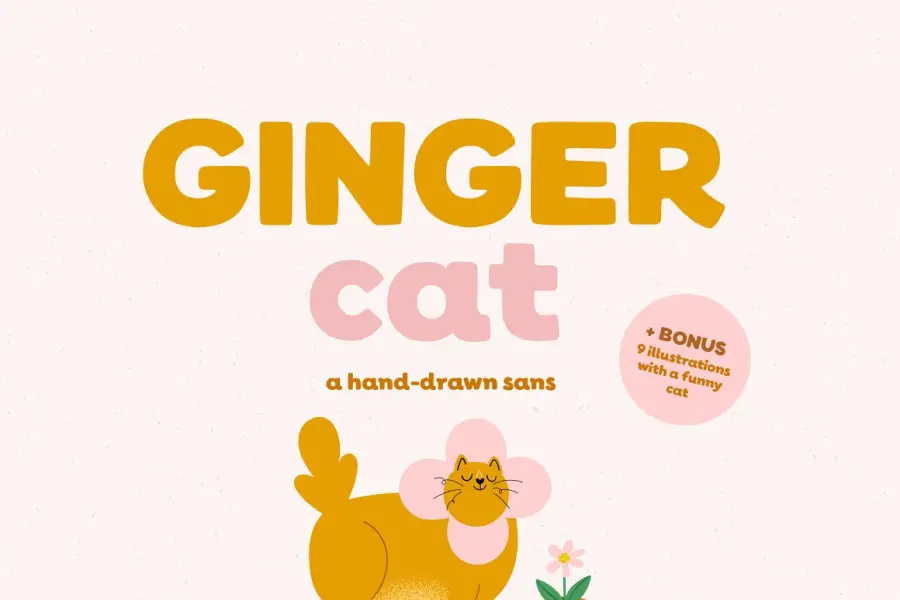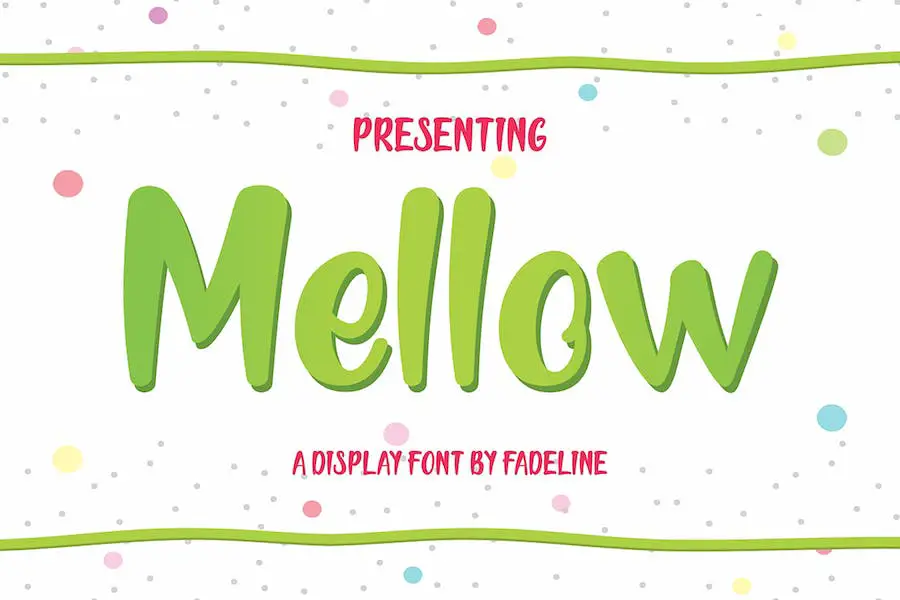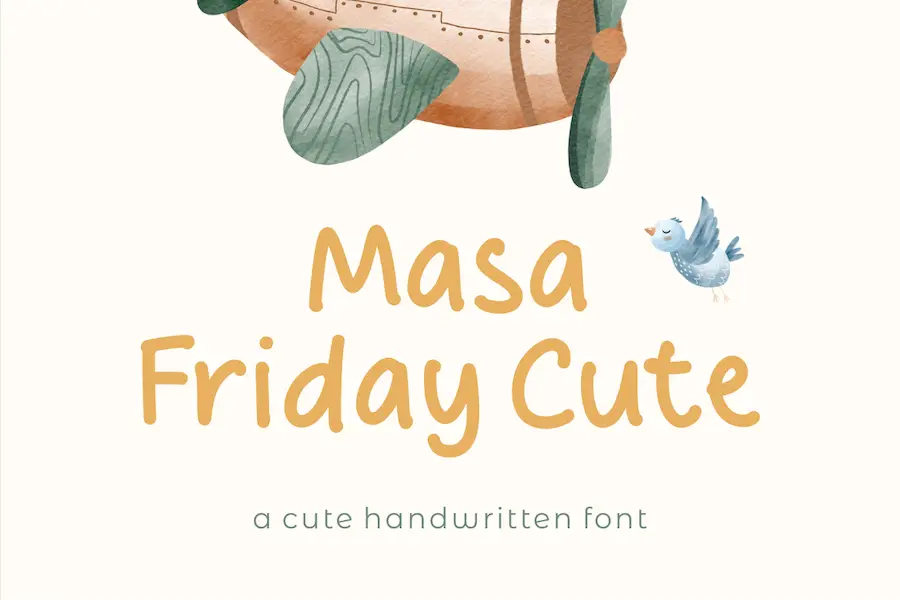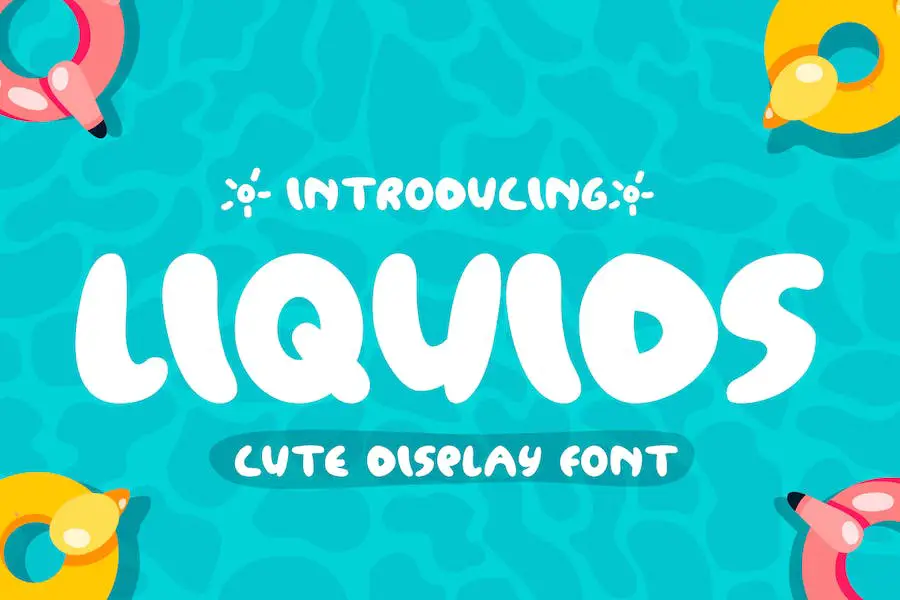
18 ฟอนต์น่ารักที่ดีที่สุด 2023 (ฟรีและพรีเมียม)
เผยแพร่แล้ว: 2023-04-20คุณเคยรู้สึกหนักใจกับตัวเลือกฟอนต์ออนไลน์ที่มีให้เลือกไม่รู้จบหรือไม่? คุณดิ้นรนเพื่อหาฟอนต์ที่น่ารักแต่ดูเป็นมืออาชีพที่เหมาะกับสไตล์ส่วนตัวของคุณหรือไม่? ไม่ต้องมองหาที่ไหนอีกแล้วเพราะเราได้รวบรวมรายชื่อแบบอักษรน่ารักที่ดีที่สุด 18 แบบที่จะช่วยเพิ่มบุคลิกภาพให้กับโครงการต่างๆ
ในบทความนี้ เราจะสำรวจแบบอักษรน่ารัก 18 อันดับแรกสำหรับทุกโอกาส ตั้งแต่รูปแบบสคริปต์ที่เขียนด้วยลายมือไปจนถึงตัวเลือกที่สนุกสนานและแปลกใหม่ เราได้รวมแบบอักษรที่หลากหลายเพื่อให้เหมาะกับทุกรสนิยม
จากการศึกษาเมื่อเร็วๆ นี้ การใช้ฟอนต์ที่มีเอกลักษณ์และสร้างสรรค์สามารถเพิ่มการมีส่วนร่วมของผู้อ่านได้มากถึง 80% ทำให้เป็นส่วนสำคัญในการออกแบบ
ไม่ว่าคุณจะออกแบบบัตรเชิญงานแต่งงาน สร้างโพสต์บนโซเชียลมีเดีย หรือแม้แต่เพียงแค่อัปเดตเรซูเม่ของคุณ การเลือกแบบอักษรที่เหมาะสมสามารถสร้างความแตกต่างได้
ดังนั้นโดยไม่ต้องกังวลใจอีกต่อไป มาดูรายชื่อฟอนต์น่ารักที่ดีที่สุด 18 แบบเพื่อเพิ่มตัวละครในโครงการต่อไปของคุณ
แบบอักษรน่ารักระดับพรีเมียมที่ดีที่สุด
บทความของเรานำเสนอฟอนต์ที่น่ารักและมีสไตล์ที่สุดที่คัดสรรมาอย่างดีสำหรับการซื้อ ฟอนต์แต่ละตัวไม่เพียงมีความสวยงามเท่านั้น แต่ยังเป็นมิตรกับผู้ใช้และใช้งานได้หลากหลาย ทำให้เหมาะสำหรับการใช้งานด้านการออกแบบที่หลากหลาย
ในบทความนี้ เราจะนำเสนอฟอนต์น่ารักระดับพรีเมียมอันดับต้น ๆ นำเสนอสถิติและข้อเท็จจริงที่น่าสนใจเกี่ยวกับผลกระทบของฟอนต์ที่มีต่อการออกแบบ และให้ภาพรวมโดยย่อเกี่ยวกับสิ่งที่ฟอนต์แต่ละตัวนำเสนอ
ดังนั้น เตรียมพร้อมที่จะเปลี่ยนการออกแบบของคุณด้วยฟอนต์ที่สนุกสนานและขี้เล่นเหล่านี้!
เรื่องร่าง
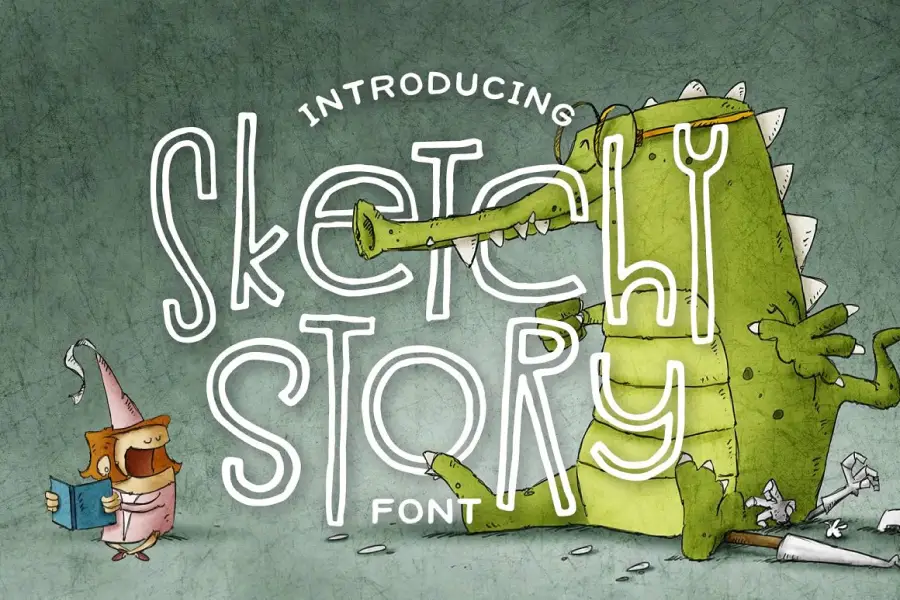
Sketchy Story เป็นฟอนต์ที่ยอดเยี่ยมที่เพิ่มความเป็นเอกลักษณ์และขี้เล่นให้กับโปรเจ็กต์ใดๆ ฟอนต์นี้มาในสองเวอร์ชัน ทั้งแบบเติมและแบบมีโครงร่าง ซึ่งสามารถใช้แยกกันหรือวางทับกันเพื่อเพิ่มความลึก นอกจากนี้คุณยังสามารถใช้แบบอักษรที่น่ารักสำหรับคำ
ขอบที่ขรุขระและรูปลักษณ์ที่บางของฟอนต์ให้ความรู้สึกเหมือนวาดด้วยมือ จึงเหมาะอย่างยิ่งสำหรับใช้ในหนังสือเด็กหรือภาพพิมพ์สถานรับเลี้ยงเด็ก มันเพิ่มบุคลิกและความสนุกสนานให้กับการออกแบบใด ๆ ให้สัมผัสที่ขี้เล่นซึ่งดึงดูดทั้งเด็กและวัยรุ่น
โดยรวมแล้ว Sketchy Story เป็นตัวเลือกที่ยอดเยี่ยมสำหรับใครก็ตามที่ต้องการเพิ่มความแปลกใหม่และความคิดสร้างสรรค์ให้กับงานของพวกเขา ความสามารถรอบด้านทำให้เป็นตัวเลือกที่ยอดเยี่ยมสำหรับโครงการที่หลากหลาย และความรู้สึกที่วาดด้วยมืออันเป็นเอกลักษณ์จะทำให้การออกแบบโดดเด่นอย่างแน่นอน
ตุ๊กตาหิมะน่ารัก
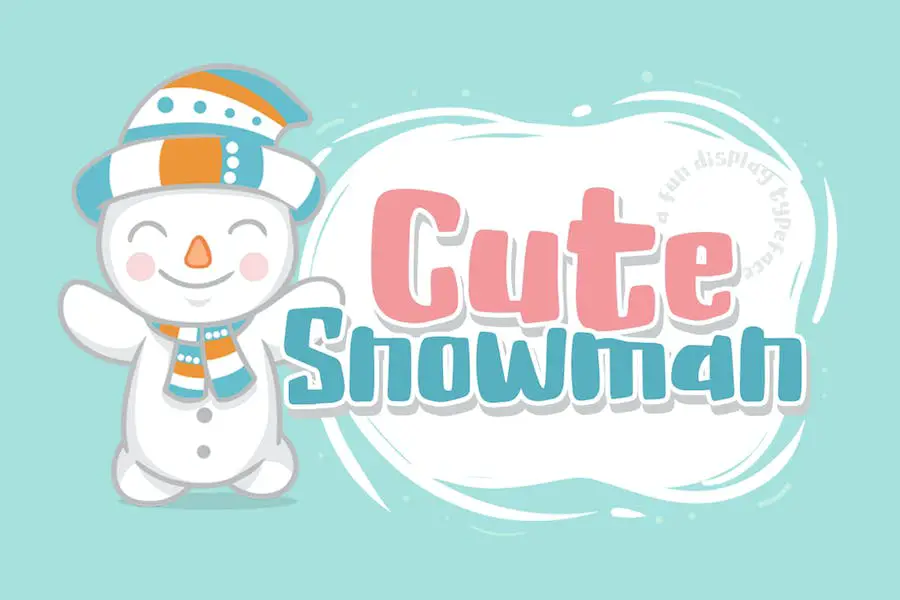
ตุ๊กตาหิมะน่ารักเป็นแบบอักษรขี้เล่นและมีสไตล์ที่สามารถเพิ่มบุคลิกภาพให้กับโครงการออกแบบใดๆ แบบอักษรที่แสดงเป็นตัวหนานี้เหมาะสำหรับการสร้างโลโก้ วัสดุสำหรับสร้างแบรนด์ การ์ดอวยพร โปสเตอร์ และอื่นๆ สไตล์ที่สนุกสนานและทันสมัยจะทำให้งานออกแบบของคุณโดดเด่นกว่าใคร
หนึ่งในคุณสมบัติที่ดีที่สุดของ Cute Snowman Font คือความสามารถรอบด้าน เหมาะสำหรับโครงการออกแบบที่หลากหลาย ตั้งแต่ความสนุกสนานและแปลกใหม่ ไปจนถึงความโดดเด่นและทันสมัย ด้วยจังหวะที่ชัดเจนและลายเส้นที่ชัดเจน ฟอนต์นี้อ่านง่ายและอ่านง่ายในทุกขนาด
อีกหนึ่งฟีเจอร์ที่ยอดเยี่ยมของ Cute Snowman Font คือรูปลักษณ์ที่สดใหม่และทันสมัย ฟอนต์มีบุคลิกเฉพาะตัวที่จะทำให้งานออกแบบของคุณมีชีวิตชีวา ไม่ว่าคุณกำลังสร้างโลโก้หรือโปสเตอร์ แบบอักษรนี้จะช่วยให้คุณสื่อสารข้อความของคุณได้อย่างสนุกสนานและมีส่วนร่วม
หวาน & โง่
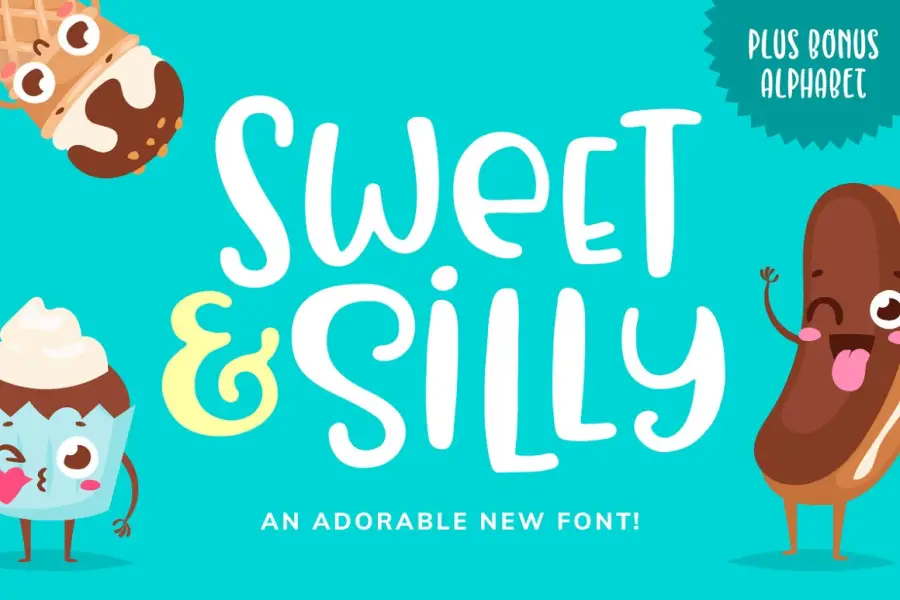
Sweet & Silly เป็นฟอนต์ที่น่ารักที่สุดที่คุณเคยเห็น! เหมาะสำหรับผู้ที่ต้องการเพิ่มความแปลกใหม่ให้กับงานออกแบบของพวกเขา ฟอนต์นี้จะทำให้คุณยิ้มได้ทุกครั้งที่ใช้ นอกจากนี้ยังเหมาะสำหรับ Adobe Cute Fonts
สิ่งที่ยอดเยี่ยมอย่างหนึ่งเกี่ยวกับ Sweet & Silly คือมีตัวอักษรภาษาอังกฤษเฉพาะตัว ซึ่งทำให้ใช้งานได้สนุกยิ่งขึ้น แบบอักษรนี้เหมาะสำหรับโครงการต่างๆ รวมถึงคำเชิญ การ์ดอวยพร และโพสต์บนโซเชียลมีเดีย ลายเส้นที่ชัดเจนและตัวอักษรที่ขี้เล่นจะทำให้ทุกโครงการโดดเด่น
พิ้งกี้น่ารัก
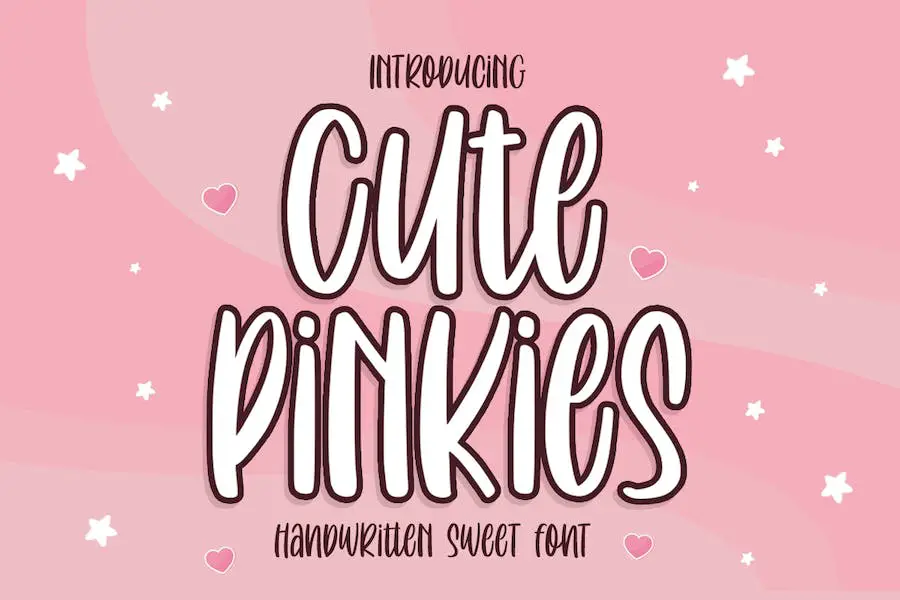
Pinkies น่ารักเป็นฟอนต์เขียนด้วยลายมือที่น่ารักและขี้เล่นซึ่งมีบรรยากาศที่อบอุ่นและเป็นกันเอง แบบอักษรนี้เหมาะสำหรับทุกคนที่ต้องการเพิ่มความน่ารักให้กับโครงการสร้างสรรค์ของพวกเขา ใช้งานได้ดีกับโพสต์ Instagram, scrapbooking, บัตรเชิญ หรือโครงการ DIY ใดๆ ที่ต้องการความเป็นส่วนตัว
หนึ่งในคุณสมบัติที่ดีที่สุดของ Pinkies น่ารักคือความสามารถรอบด้าน ฟอนต์มีทั้งแบบปกติและแบบหนา ซึ่งช่วยให้คุณสร้างงานออกแบบได้หลากหลายโดยใช้ฟอนต์เดียว คุณสามารถใช้พาดหัวข่าว เนื้อความ หรือแม้แต่เป็นลายเซ็น
ฟอนต์ยังประกอบด้วยตัวพิมพ์เล็กและตัวพิมพ์ใหญ่ ตัวเลข และเครื่องหมายวรรคตอนทั่วไป ทำให้ง่ายต่อการใช้ในการออกแบบใดๆ
ปุย Monsta
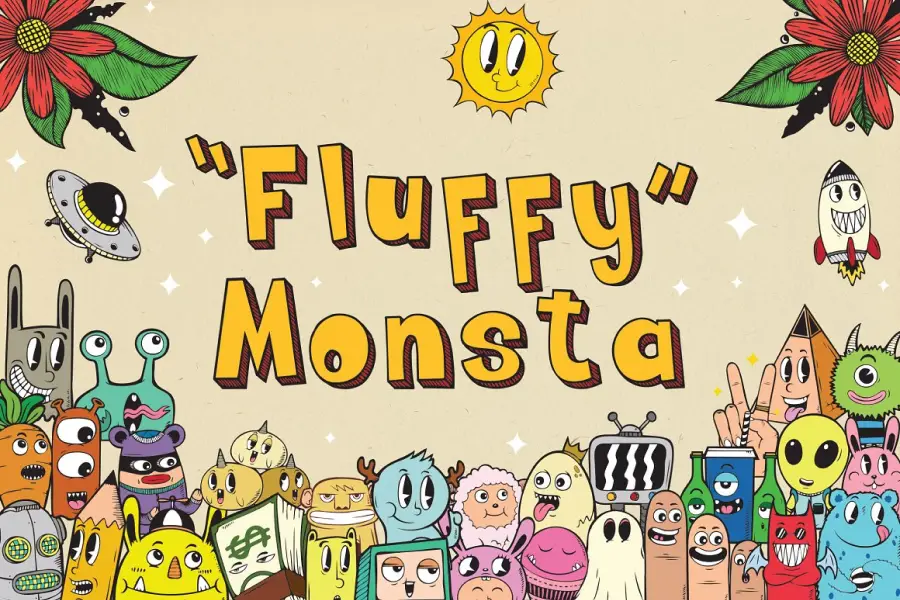
Fluffy Monsta เป็นฟอนต์ Doodle สุดน่ารักที่สามารถใช้งานได้หลากหลาย เหมาะสำหรับสติกเกอร์ โลโก้ ตราสัญลักษณ์ แบบโลโก้ ลายเส้น การ์ด การโฆษณา และอื่นๆ อีกมากมาย เป็นฟอนต์อเนกประสงค์ที่ตอบสนองความต้องการด้านการออกแบบที่แตกต่างกัน
คุณสมบัติที่โดดเด่นอย่างหนึ่งของ Fluffy Monsta คือความน่ารัก ฟอนต์นี้ออกแบบโดยคำนึงถึงความแปลกใหม่ เพิ่มลูกเล่นให้กับโปรเจ็กต์ที่ใช้ นอกจากนี้ ความรู้สึกที่วาดด้วยมือของฟอนต์ยังทำให้การออกแบบมีคุณภาพที่เป็นธรรมชาติซึ่งหาได้ยากในฟอนต์อื่นๆ
คุณสมบัติที่ยอดเยี่ยมอีกอย่างของ Fluffy Monsta คือความยืดหยุ่น ด้วยการใช้งานที่เป็นไปได้มากมาย นักออกแบบจึงมั่นใจว่าจะหาวิธีรวมฟอนต์นี้เข้ากับงานของพวกเขาได้ ไม่ว่าคุณจะออกแบบโลโก้หรือสร้างป้ายสนุกๆ ฟอนต์นี้ช่วยคุณได้
กอริลลาน่ารัก
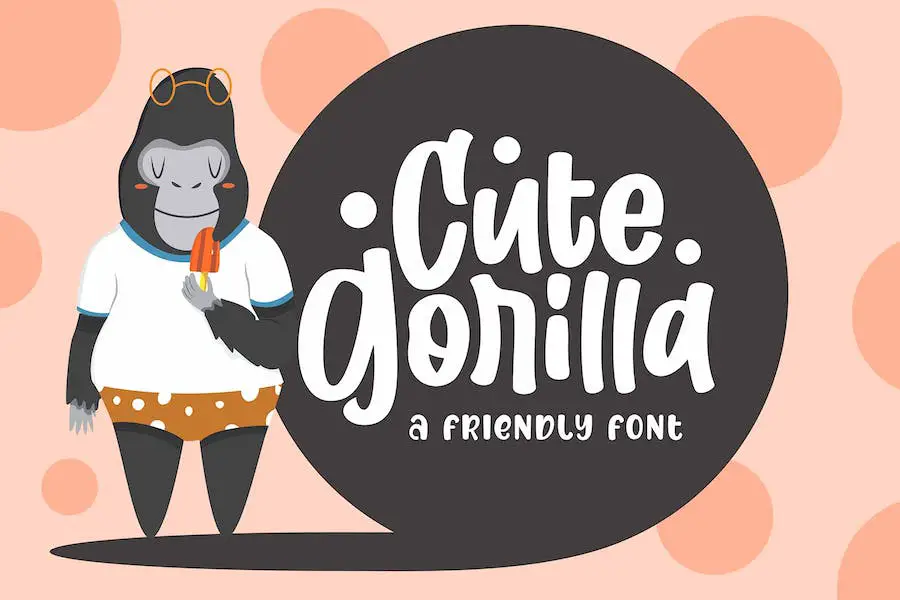
กอริลลาน่ารักเป็นหนึ่งในแบบอักษรน่ารักที่เหมาะสำหรับโครงการออกแบบต่างๆ ด้วยสไตล์ขี้เล่นและความรู้สึกเชิญชวน มันจึงเป็นตัวเลือกที่ยอดเยี่ยมสำหรับทุกคนที่ต้องการยกระดับการสร้างแบรนด์ หัวเรื่อง การออกแบบงานแต่งงาน การ์ดเชิญ ลายเซ็น โลโก้ ป้ายกำกับ และอื่นๆ อีกมากมาย